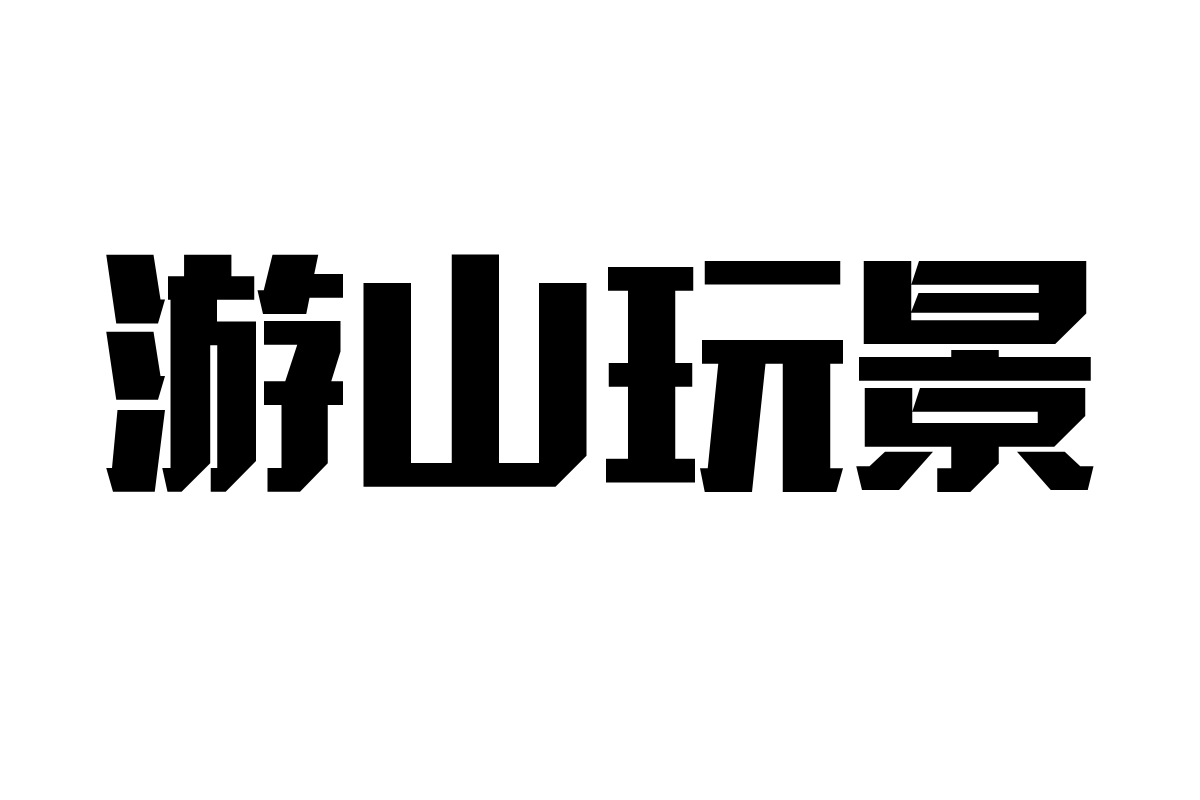
汉仪铸字超然体是一款具有独特风格的中文字体,其特点是字形简洁、线条流畅,给人一种超然脱俗的感觉。这款字体适用于各种需要展示清晰、易读性的文字设计,如标题、正文、广告等。
汉仪铸字超然体的笔画粗细均匀,结构紧凑,给人一种稳重而不失灵动的感觉。在视觉上,这种字体能够很好地平衡文字的清晰度和美观度,使读者在阅读过程中能够轻松地获取信息。
此外,汉仪铸字超然体还具有较好的适应性,无论是在哪种尺寸下都能保持清晰的视觉效果。这使得它成为许多网页设计和印刷品制作中的首选字体之一。
总的来说,汉仪铸字超然体是一款适合现代设计需求的中文字体,无论是用于商业还是艺术类的设计项目,都能够展现出其独特的魅力。